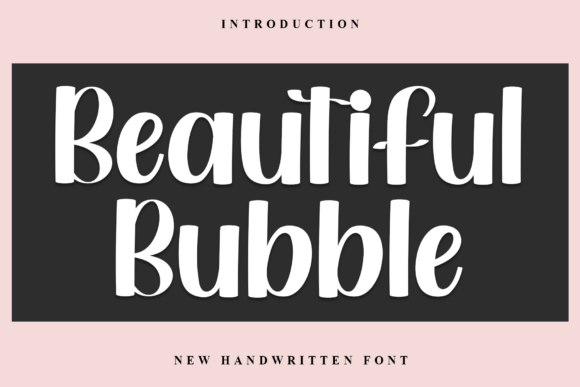
Beautiful Bubble
Beautiful Bubble : la police qui fait pétiller vos créations
Vous cherchez une police casual et créative pour apporter chaleur et convivialité à vos projets ? Beautiful Bubble est la réponse idéale. Avec ses traits ronds et ludiques, elle crée une ambiance détendue et accueillante, parfaite pour les invitations, les publications sur les réseaux sociaux, les cartes de vœux et tout autre support personnel.
- Style unique : design hand‑drawn qui donne un aspect artisanal et charmant à chaque texte.
- Facilité d’utilisation : idéale pour les débutants comme pour les designers confirmés qui souhaitent ajouter une touche de fun à leurs visuels.
- Impact visuel : les courbes douces et les formes arrondies captent immédiatement l’attention et transmettent une sensation de proximité.
Que vous prépariez une invitation d’anniversaire, un post Instagram accrocheur ou un flyer pour un événement local, Beautiful Bubble vous permet de créer des designs qui se démarquent tout en restant chaleureux et accessibles. N’attendez plus, téléchargez dès maintenant cette police et donnez à vos projets le côté « bubble‑tastic » qui fera sourire votre audience !